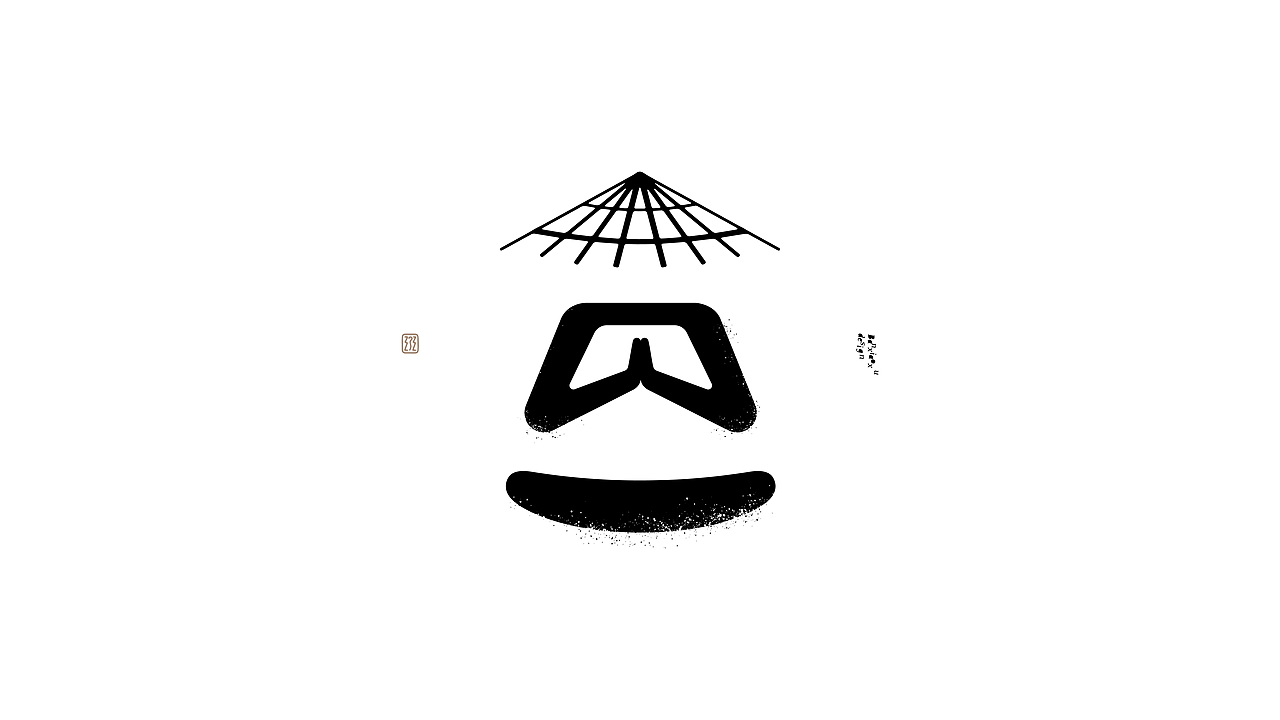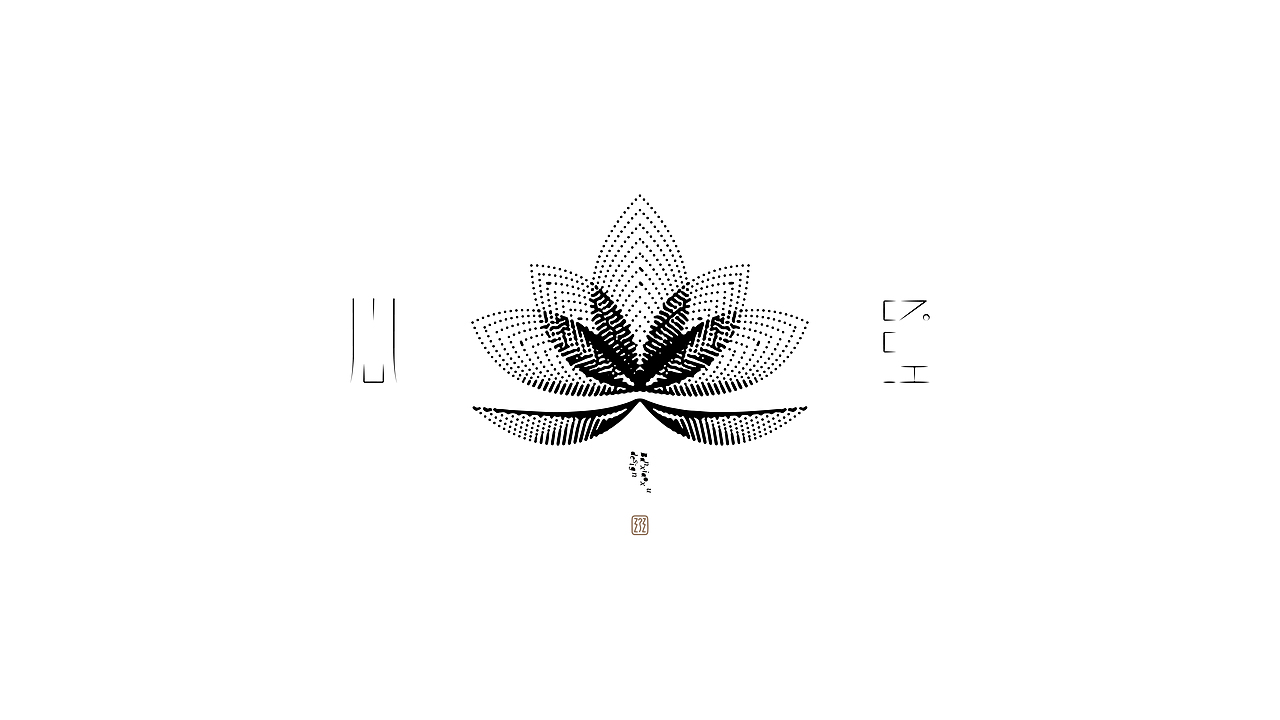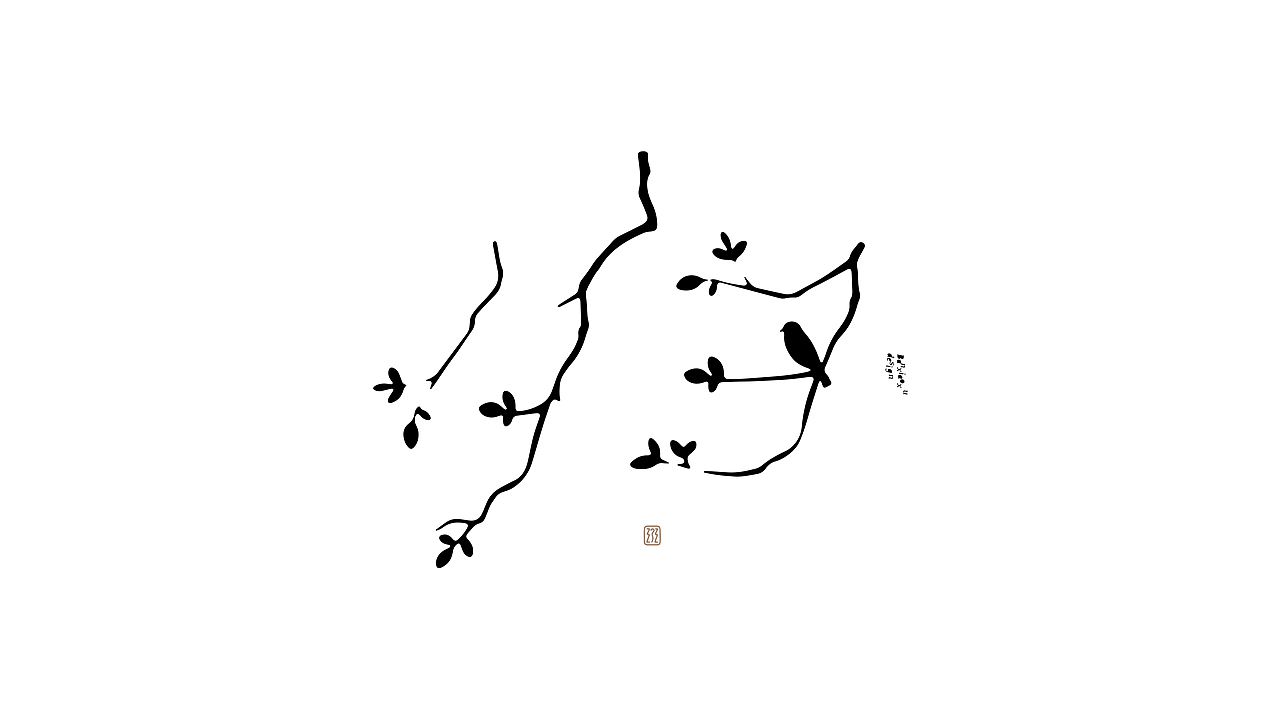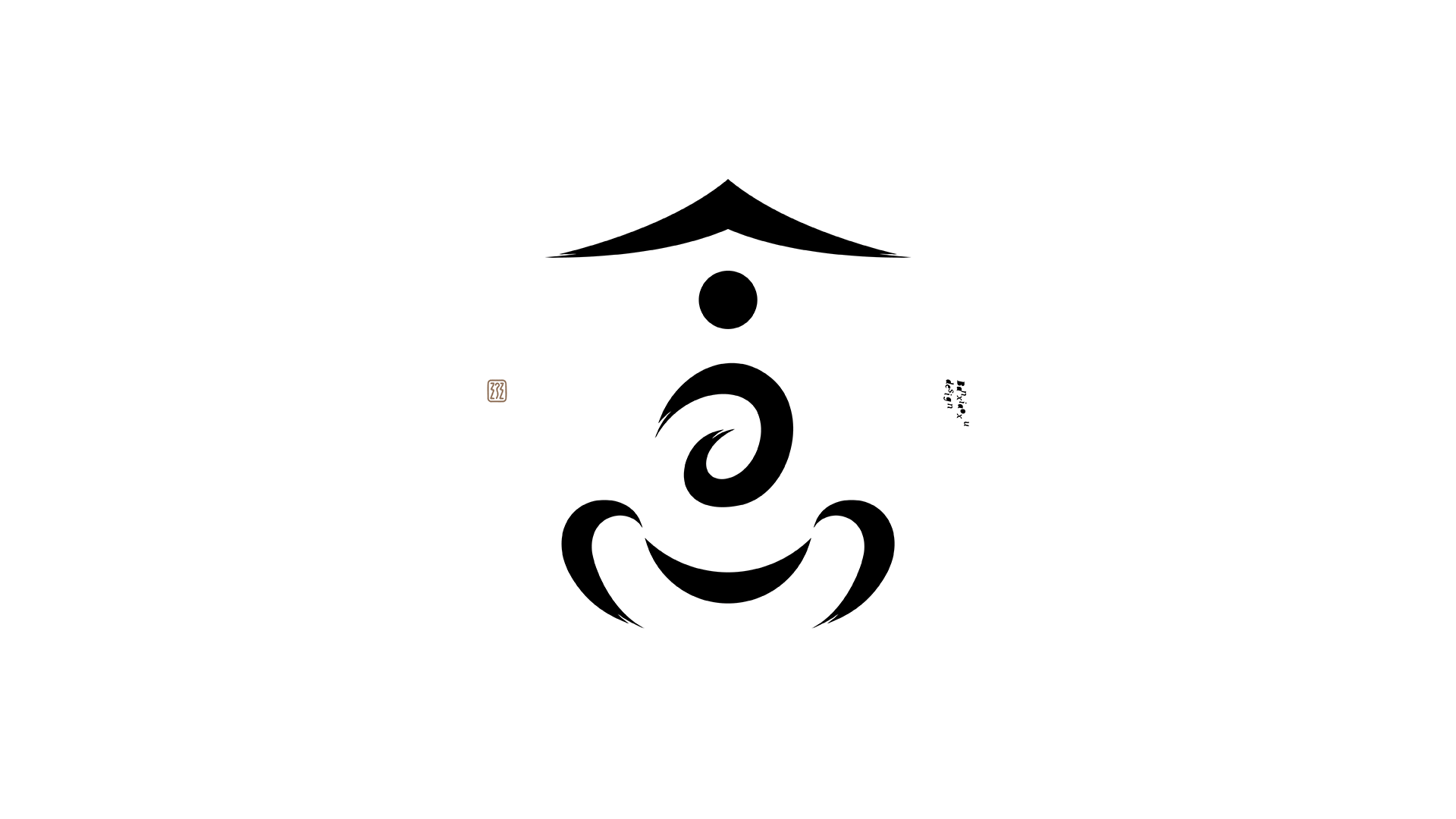
字体结构与创意(二十五)
• 自由
• 就像风中的烛火
• 一是开始
• 也是结束
• 一直在思考死亡
• 或许平静的时候
• 就是躺在棺木里
字体结构与创意第二十五系列的感思
忽然发现原来这个系列已经第六年了
坐忘
自由,风中的烛火
路很多,但又好像又没有
相连
染布之后晾晒在竹竿上
骂也是一种沟通方式
他乡的鸟儿归往来时路
一是开始,也是结束,就像生命的来时与归去
秩序与不同
花,鸟虫
窗格的回忆
源而不同
班,心有猛虎
贪嗔痴
心经
禅坐
念禅
欲穷千里目,更上一层楼
无竹